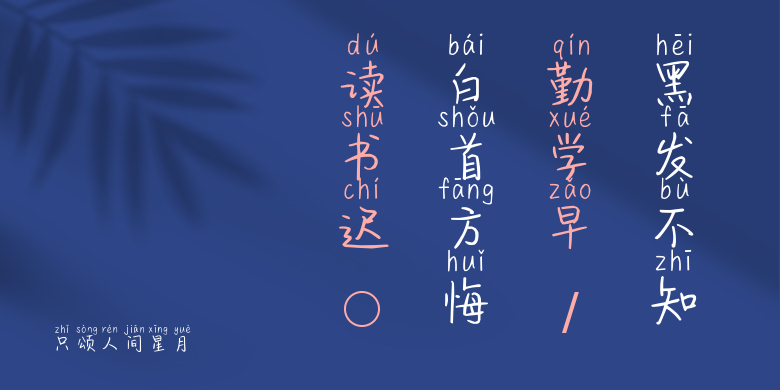
只颂人间星月
只颂人间星月,这款字体结构工整、笔画清晰,兼顾美观与易读性,适用于标题、正文、海报、包装、LOGO 等多种场景。字形优雅稳定,风格百搭耐看,适配日常排版与创意设计,让文字呈现更舒适、更具质感。只颂人间星月一笔一画,皆是细节,以均衡的比例、流畅的线条打造舒适视觉体验,字形端正大气,风格简约现代。无论是商业设计、品牌宣传还是日常排版,都能轻松驾驭,让文字更有格调与力量。只颂人间星月字体下载。